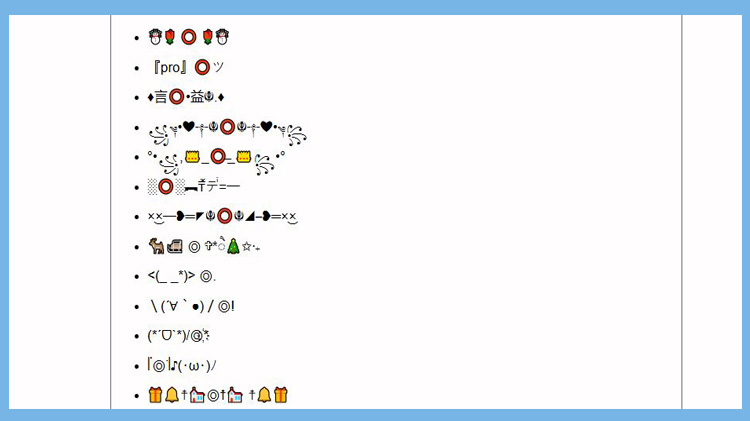
100+ Kiểu chữ O kí tự đặc biệt phổ biến, đẹp, in hoa, viết thường, emoji
Chữ O kí tự đặc biệt là phiên bản cách điệu của chữ O thông thường, được tạo từ các ký tự thuộc bảng mã Unicode. Những ký tự này thường được dùng để làm nổi bật tên người dùng trong game, mạng xã hội.
Trong bài viết dưới đây, MobiFonts sẽ cùng các bạn khám phá 100+ chữ O kiểu kí tự đặc biệt phổ biến, đẹp, in hoa, viết thường, emoji. Ngoài ra, chúng tôi sẽ giải đáp cho bạn một số câu hỏi thường gặp về loại kí tự này.
Chữ O kí tự đặc biệt là một trong những dạng biến thể được ưa chuộng để tạo điểm nhấn trong tên game, bài đăng mạng xã hội. Các kiểu chữ O cách điệu đều được mã hóa theo chuẩn Unicode quốc tế, đảm bảo khả năng hiển thị ổn định trên đa số thiết bị. Dưới đây là một số kí tự chữ O phổ biến và được nhiều người lựa chọn sử dụng nhiều nhất:
Nếu bạn đang tìm kiếm một chữ O vừa đẹp vừa có phong cách độc lạ thì dưới đây là một số gợi ý dành cho bạn:
Kí tự đặc biệt chữ O in hoa là những biến thể cách điệu của chữ “O” viết hoa, được tạo bằng mã Unicode để trông nổi bật, nghệ thuật hoặc mang phong cách khác biệt. Một số ví dụ về kí tự chữ O in hoa như sau:
Chữ o viết thường khi được cách điệu dưới dạng kí tự đặc biệt sẽ mang đến phong cách mới mẻ, độc đáo cho tên hiển thị trong mạng xã hội, game online hay các bài viết sáng tạo. List dưới đây gợi ý các kiểu chữ o kí tự đặc biệt:
Chữ O kiểu emoji là các ký tự mang hình dáng giống chữ O được mã hóa dưới dạng biểu tượng cảm xúc thường có màu sắc và kiểu dáng nổi bật như hình tròn đỏ 🔴, trắng ⚪, hoặc viền tròn Ⓞ. Những emoji này giúp gây ấn tượng mạnh cho người xem trên các nền tảng mạng xã hội, trò chơi điện tử và thiết kế đồ họa. Dưới đây là một số emoji hình dáng chữ O mà bạn có thể tham khảo: